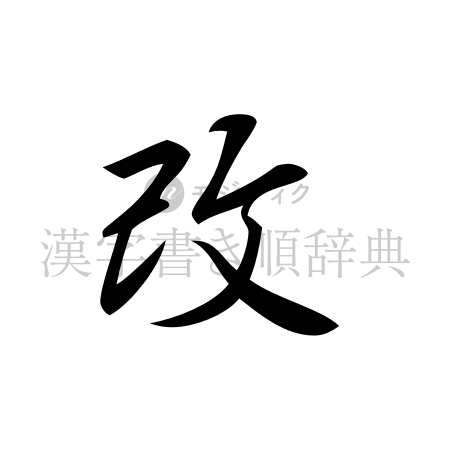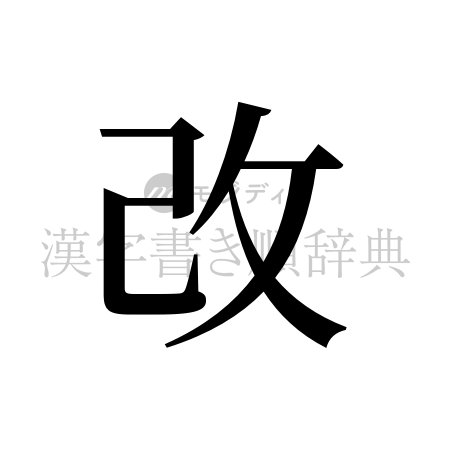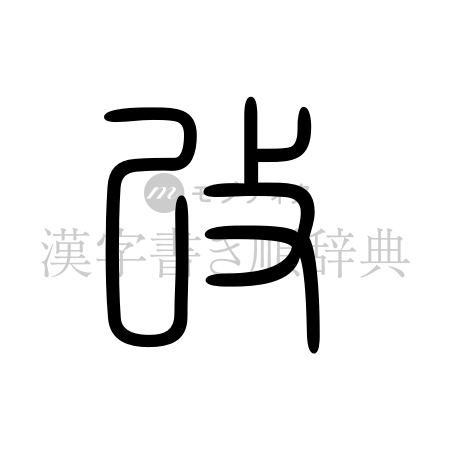
漢字「改」(おのれに攵)の書き順・読み方・意味・部首・画数
「改」の読み・画数の基本情報
「改」の書体
「改」に形の似た漢字
「改」の意味
- あらためる。あらたまる。
- なおす。なおる。
- 変える。変わる。
- 正す。
- 新しくする。
- 改善する。
- 修正する。
- 改良する。
- 改定する。
- 改正する。
「改」の意味の英訳
漢字は1文字で多様な意味を持ちますが、「改」を英語で表す場合、一般的には reformation, change, modify, mend, renew, examine, inspect, search などがあります。
「改」の成り立ち・由来
| 構造 | 意符攵(動作)+音符己 |
「攵(攴)」と「己」を組み合わせた形声文字です。右の「攵」は手に道具を持って打つさまをかたどり、手を加える動作を表す意符です。左の「己」は音符として、字の読みを示す役割を担うと考えられます。両者が合わさって、手を加えて正しくする、古いものをあらためて新しくするという意味を表しました。『説文解字』にも「更なり」とあり、あらためる・なおすの意で用いられてきました。なお、「己」に自らの過ちの意を読み取り、それを打って正すとみる会意的な解釈もあり、諸説あります。
※ 「己」を音符とする形声説のほか、自らの過ちを打って正すとする会意的解釈もあり、諸説あります。
- 改革 - かいかく
- 基盤は維持しつつ、社会制度や機構・組織などをあらため変えること。
- 改心 - かいしん
- 今までのことを反省し、心を改め正すこと。
- 改新 - かいしん
- 古い制度や規則、習慣などを改めて新しくすること。